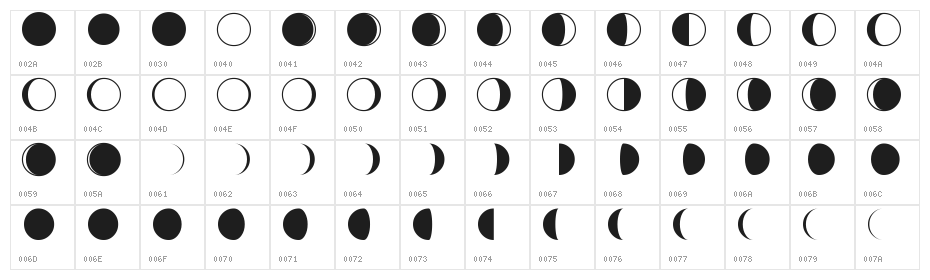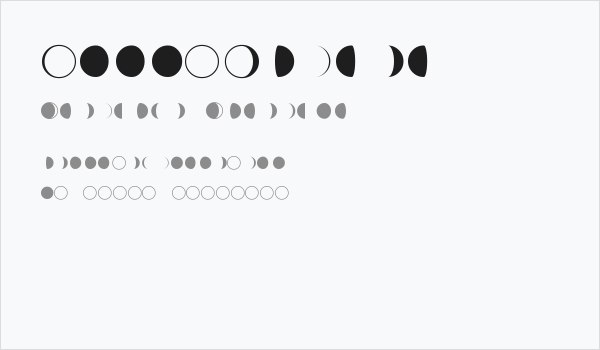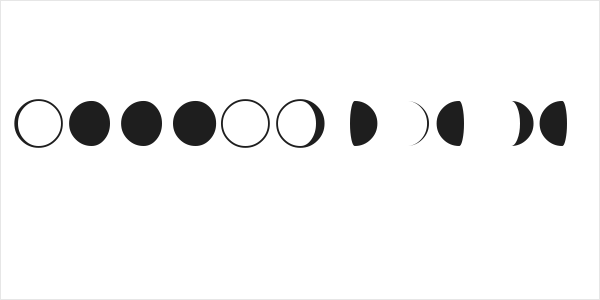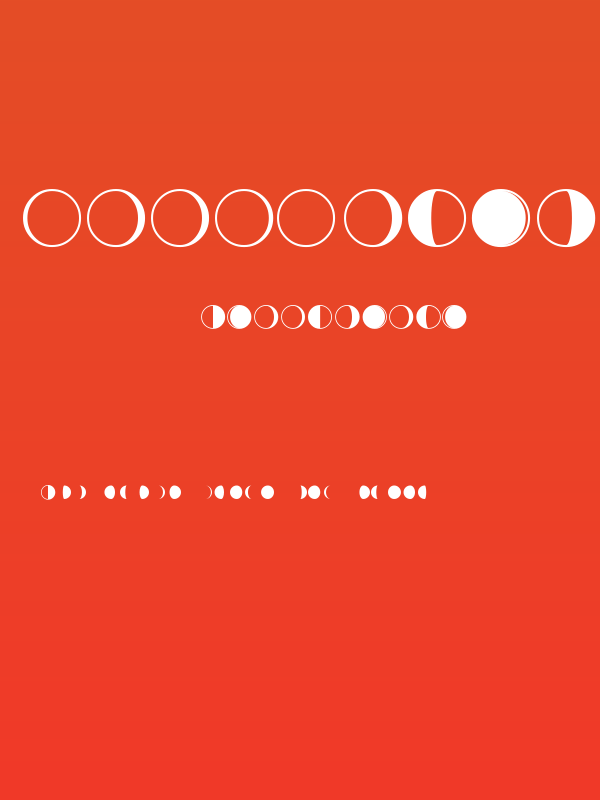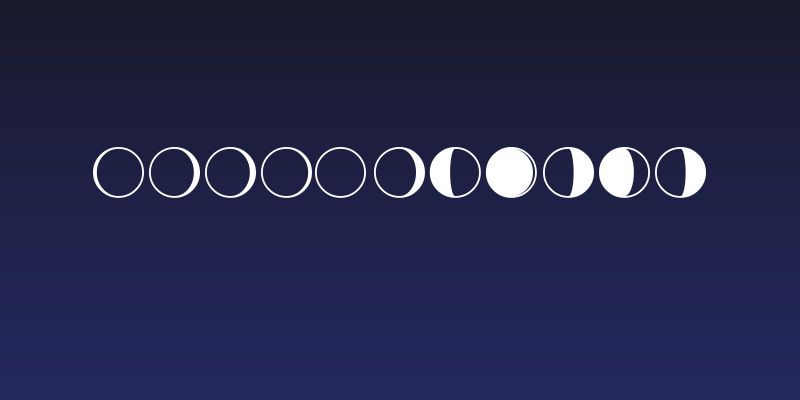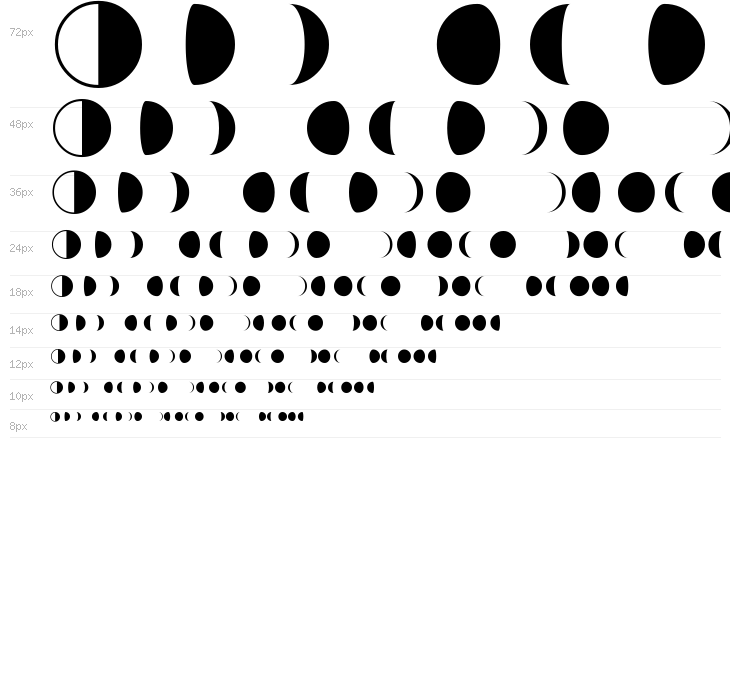
Moon-Phases Font
Questo font include 62 caratteri. Clicca su un carattere per vedere i dettagli.
| Stile generale | Minimalistic, symbolic |
| Caso d'uso | Decorative elements, thematic designs, logos related to moon or night themes |
| Progetti proposti | Astrology or astronomy themed designs, decorative borders, celestial event promotions, and artistic projects involving lunar imagery. |